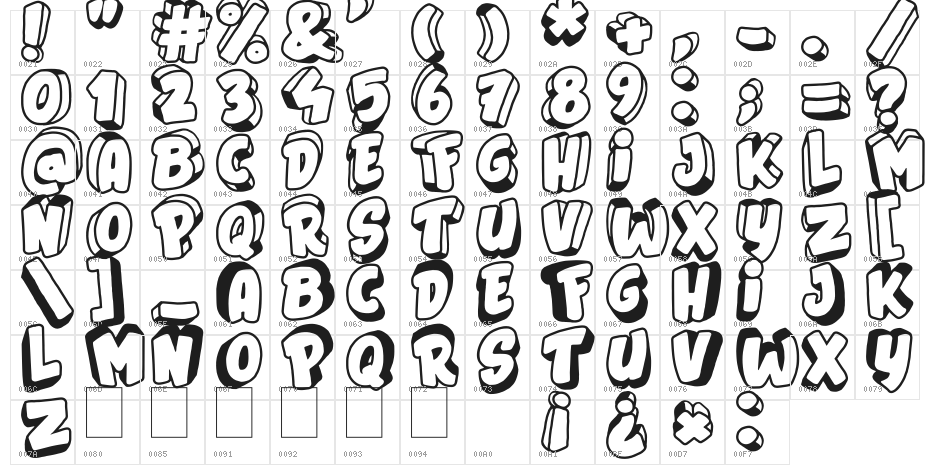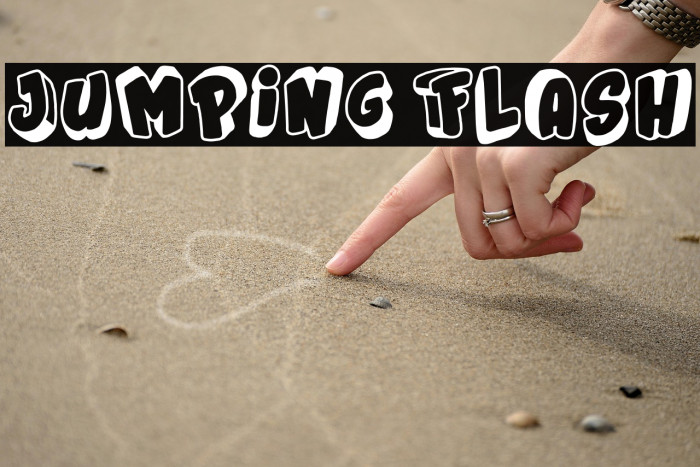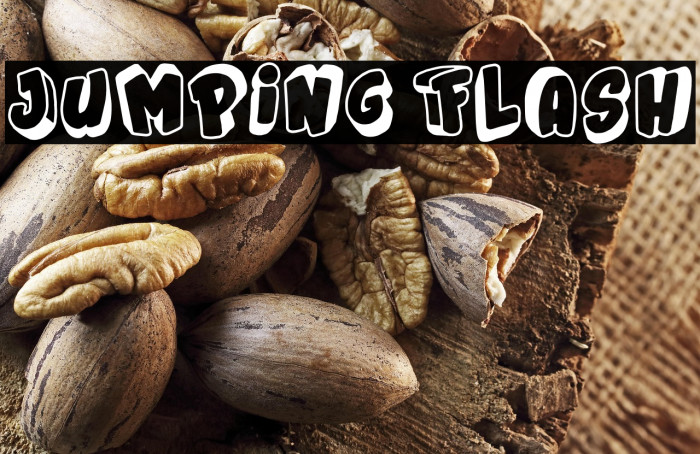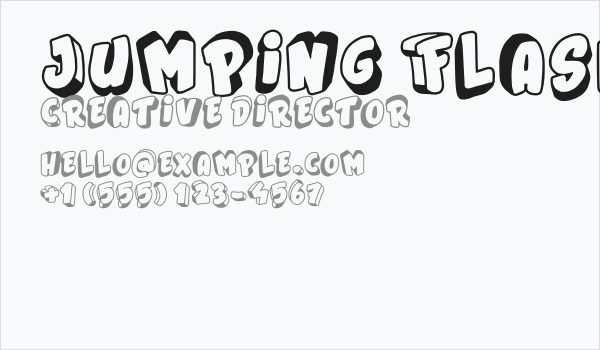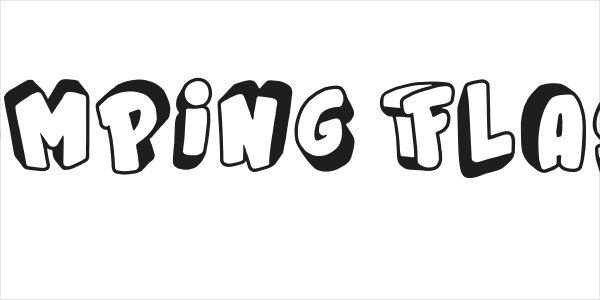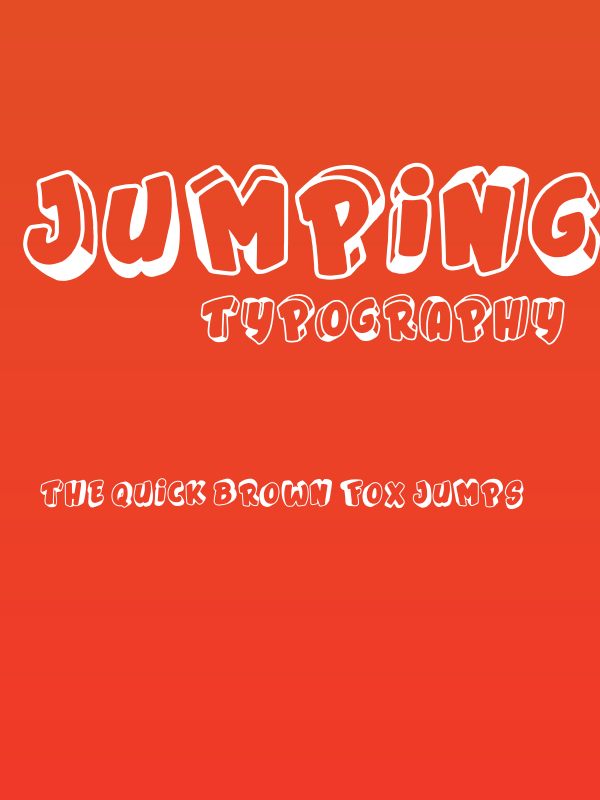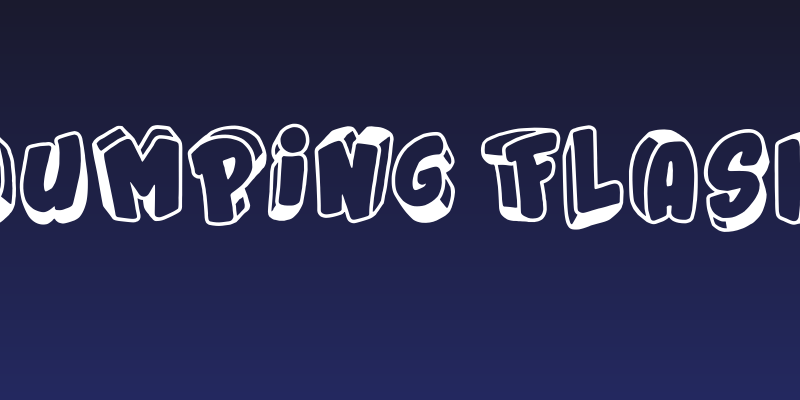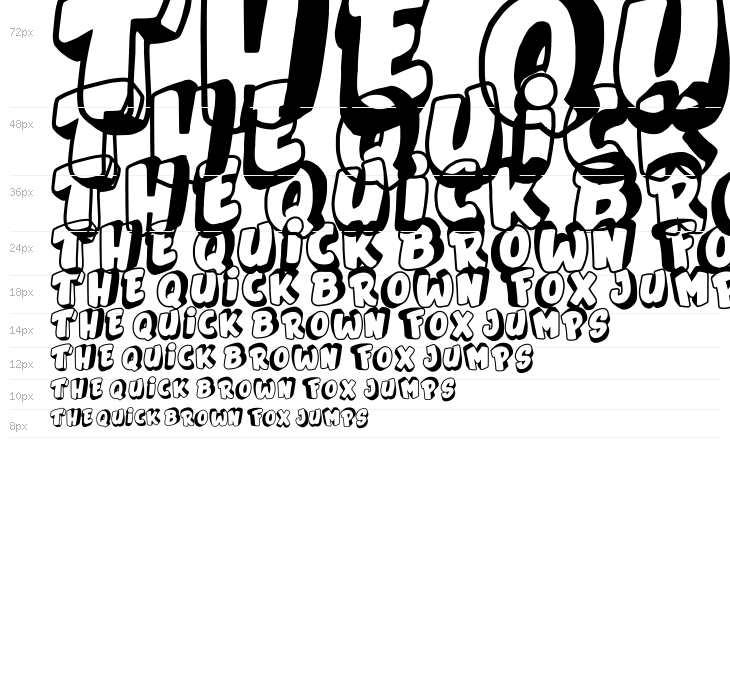
Jumping Flash Font
| Estilo general | Playful, Cartoonish, Energetic |
| Caso de uso | Headlines, Logos, Posters, Children's Materials |
| Proyectos propuestos | Ideal for children's books, comic strips, playful branding, party invitations, and any project needing a fun, lively touch. |